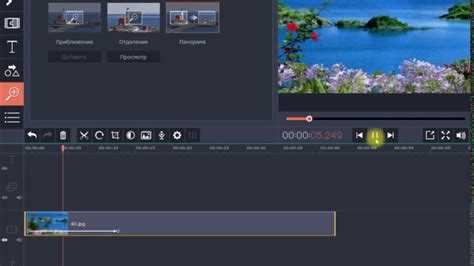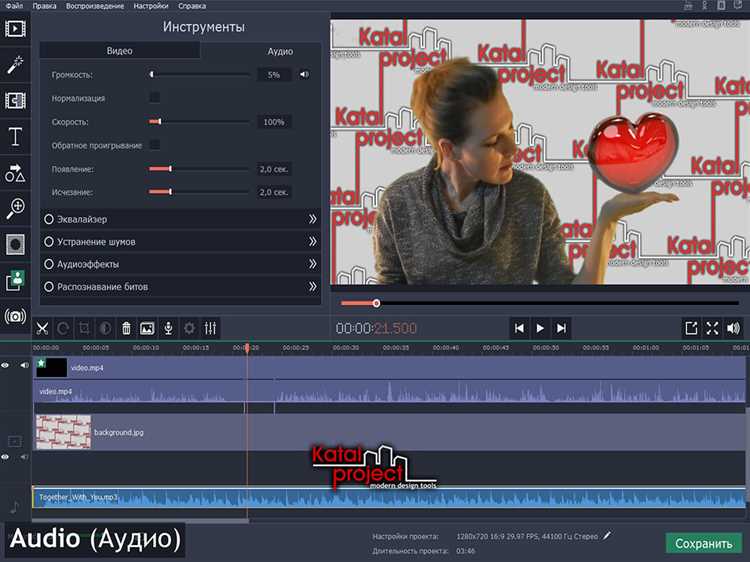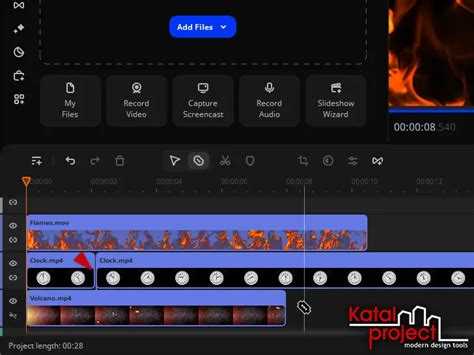
Добавление огненного шрифта в видеоролик – это способ моментально привлечь внимание зрителя и подчеркнуть драматичную или динамичную атмосферу сцены. В Movavi Video Editor реализовать такой эффект можно с помощью встроенных инструментов анимации, эффектов свечения и сторонних графических элементов. Не требуется установка дополнительных плагинов или сложная постобработка.
Для начала подготовьте текстовую вставку через вкладку «Титры». Выберите минималистичный шрифт без засечек – он лучше визуализируется в сочетании с огненным эффектом. После размещения текста на таймлайне примените к нему эффект «Пламя» или «Светящееся свечение» из библиотеки спецэффектов. Отрегулируйте параметры насыщенности, прозрачности и цветовой температуры, чтобы добиться реалистичного жаркого оттенка.
Далее включите анимацию появления – оптимально подойдут типы «Вспышка» или «Появление с искрами», если они доступны в вашей версии Movavi. Чтобы усилить эффект, добавьте аудиосопровождение: короткий звук зажигания или треск пламени. Завершите обработку легким затемнением фона или применением фильтра «Темное небо», чтобы текст с огненным эффектом выглядел контрастно и объемно.
Экспортируйте видео в формате MP4 с высоким битрейтом, чтобы сохранить качество анимации. При необходимости текст с огнем можно наложить поверх основного видео с помощью режима наложения «Добавить» или «Экран» – это особенно актуально, если вы используете готовую анимацию огня с прозрачным фоном.
Выбор и установка подходящего шрифта с огненной стилизацией
Для создания огненного эффекта в Movavi потребуется шрифт с агрессивной, резкой или плавящейся формой букв. Подойдут гарнитуры с острыми краями, имитацией языков пламени или трещин. Рекомендуемые варианты: «Flame», «Firestarter», «Burnout», «Incinerator». Эти шрифты доступны на сайтах dafont.com, 1001fonts.com и fontspace.com. Убедитесь, что формат файла – .ttf или .otf.
Для большей выразительности подбирайте шрифт с учётом фона видео. На тёмном фоне хорошо работают шрифты с тонкими, изломанными линиями, а на светлом – массивные буквы с эффектом расплавленного металла. Используйте только латиницу – большинство декоративных огненных шрифтов не поддерживают кириллицу.
Импорт текста в Movavi и настройка его базовых параметров
Откройте проект в Movavi Video Editor и переместитесь на вкладку «Титры» в левой панели. Выберите шаблон, максимально приближённый к будущему огненному эффекту – подойдут стили с жирным шрифтом и простой анимацией. Перетащите выбранный титр на временную шкалу, в нужное место видеоряда.
Дважды щёлкните по титру на таймлайне, чтобы открыть панель редактирования. В текстовом поле введите нужную фразу. Используйте заглавные буквы – они лучше воспринимаются в визуально насыщенных эффектах, особенно с огненным оформлением.
Перейдите в раздел шрифтов. Рекомендуется выбирать прямые, массивные шрифты без засечек: Impact, Arial Black, Franklin Gothic Heavy. Такие шрифты обеспечивают лучшую читаемость в сочетании с анимированными эффектами огня.
Установите максимальный размер шрифта, не выходящий за границы кадра. При необходимости измените положение текста, чтобы он находился в центре или нижней трети кадра – в зависимости от композиции. Переходите к настройке цвета: на этом этапе задайте белый или светло-жёлтый – они лучше взаимодействуют с последующими огненными фильтрами.
Выключите тени и обводку, если они есть по умолчанию, чтобы не исказить эффект огня. В завершение, установите продолжительность отображения текста, точно определив начало и конец – слишком долгий показ снижает выразительность будущей анимации.
Применение анимации для имитации движения огня
Для реалистичного эффекта огненного шрифта в Movavi важно задействовать ключевые кадры и параметры анимации. Начните с наложения огненной текстуры поверх текста с прозрачным фоном. Используйте видеофайл с движением пламени или GIF-анимацию в формате .mov или .png с альфа-каналом.
В панели «Анимация» выберите режим «Пользовательская анимация». Установите два ключевых кадра: начальный – с текстурой огня в исходной позиции, конечный – со смещением, масштабированием и легким вращением. Это создаст эффект пульсации и «живости» пламени.
Задайте циклическое повторение анимации, чтобы огонь не замирал. Регулируйте параметры прозрачности и наложения, используя режимы смешивания «Осветление» или «Экран». Это обеспечит органичное слияние текстуры пламени с буквами.
Сколько времени занимает создание огненного текста в Movavi, если делать это впервые?
Впервые создание огненного шрифта может занять от 20 до 40 минут. Время зависит от вашего опыта работы с редактором и сложности задуманного эффекта. На первых этапах стоит уделить внимание выбору подходящего шрифта, затем – правильному наложению огненных эффектов и цветокоррекции. С практикой процесс значительно ускоряется.